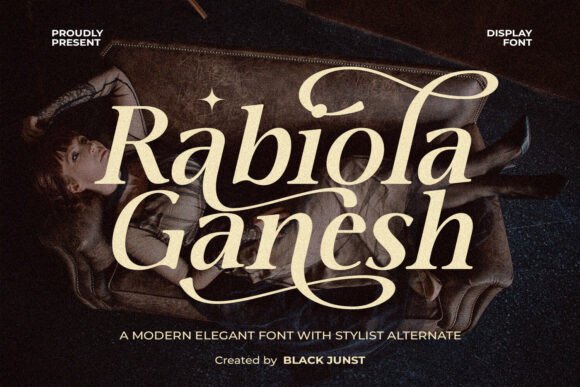
Rabiola Ganesh
適切なデザイン要素を見つけるのは難しい場合がありますが、Rabiola Ganeshは作品を即座に引き立てる優れたコレクションを提供します。
POD(オンデマンド印刷)製品、結婚式の招待状、またはソーシャルメディアのグラフィックを作成している場合でも、Rabiola Ganeshは理想的です。